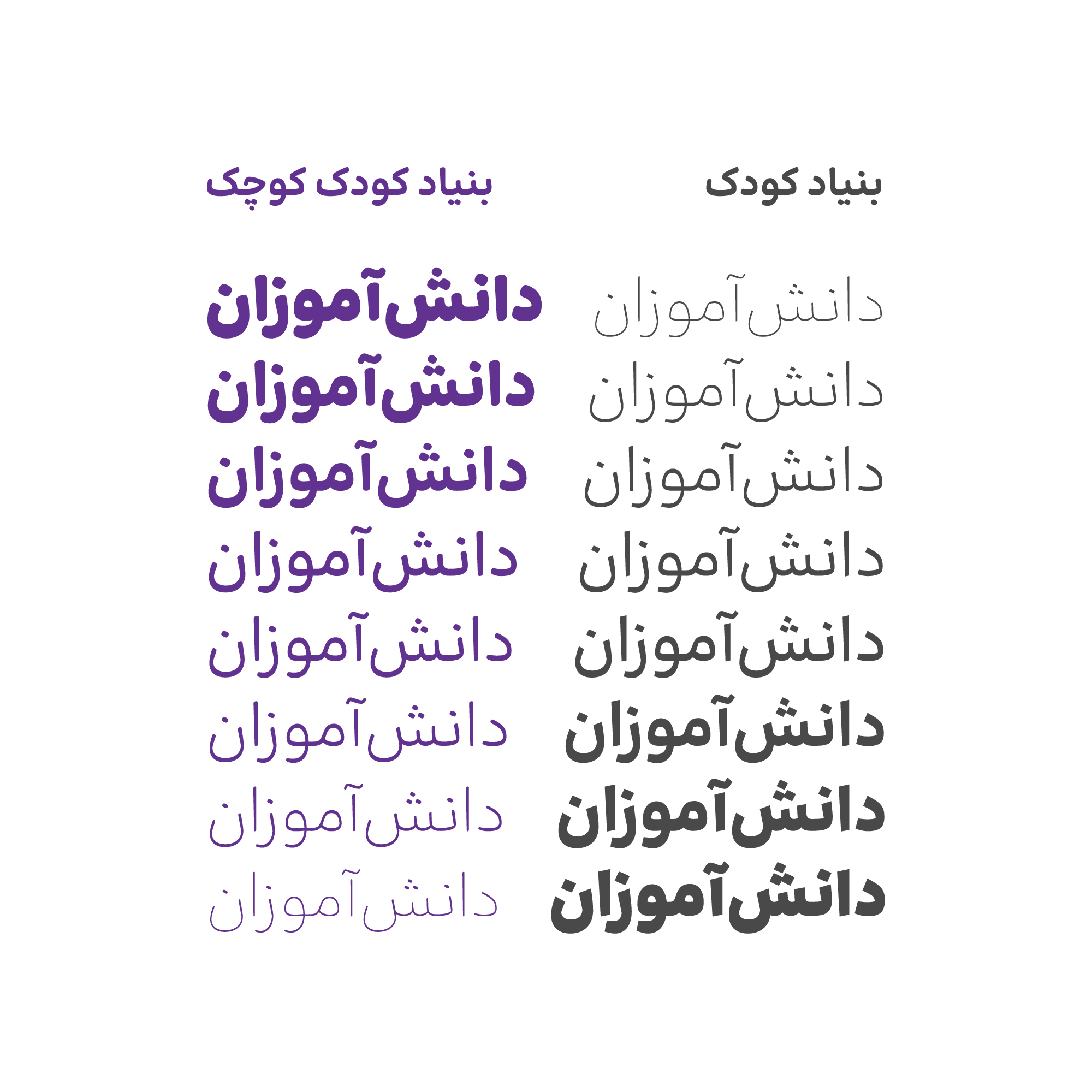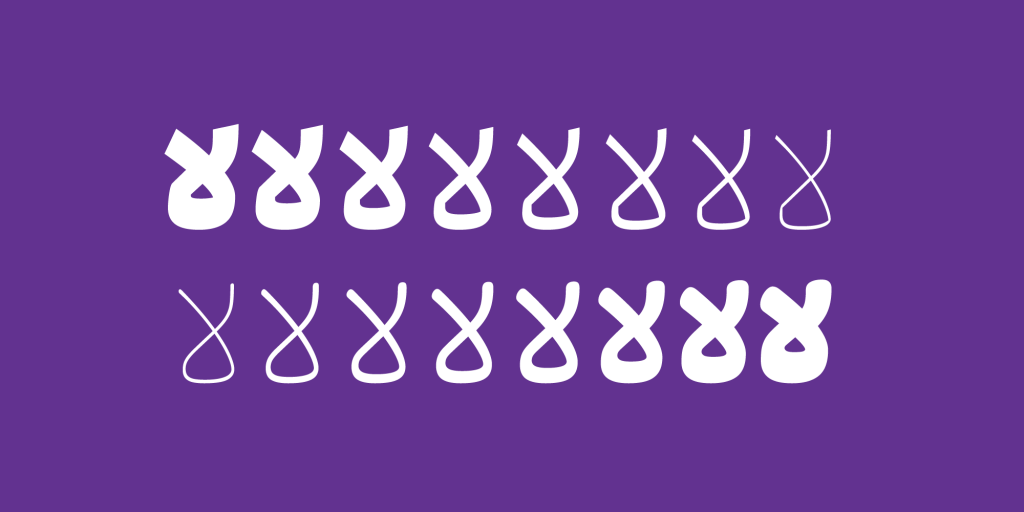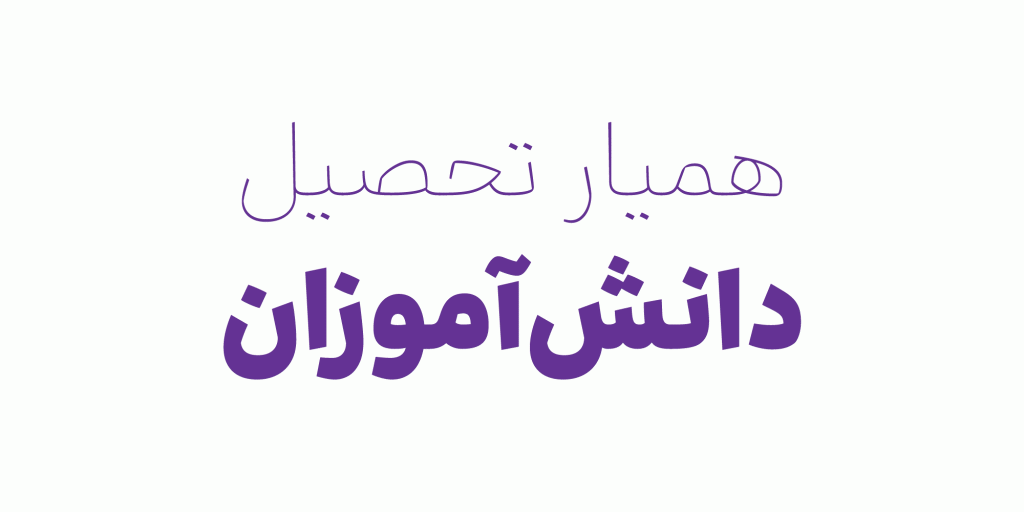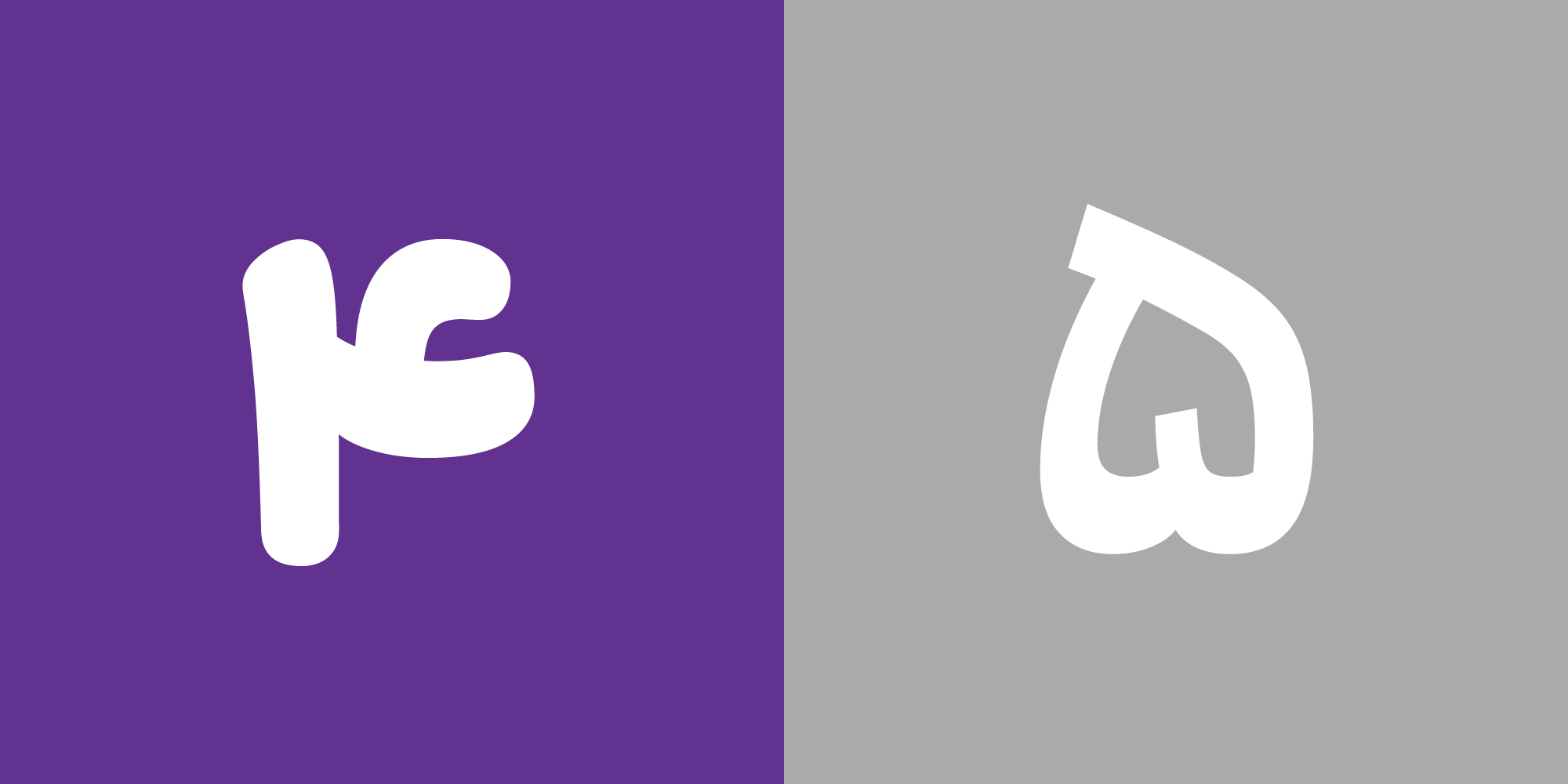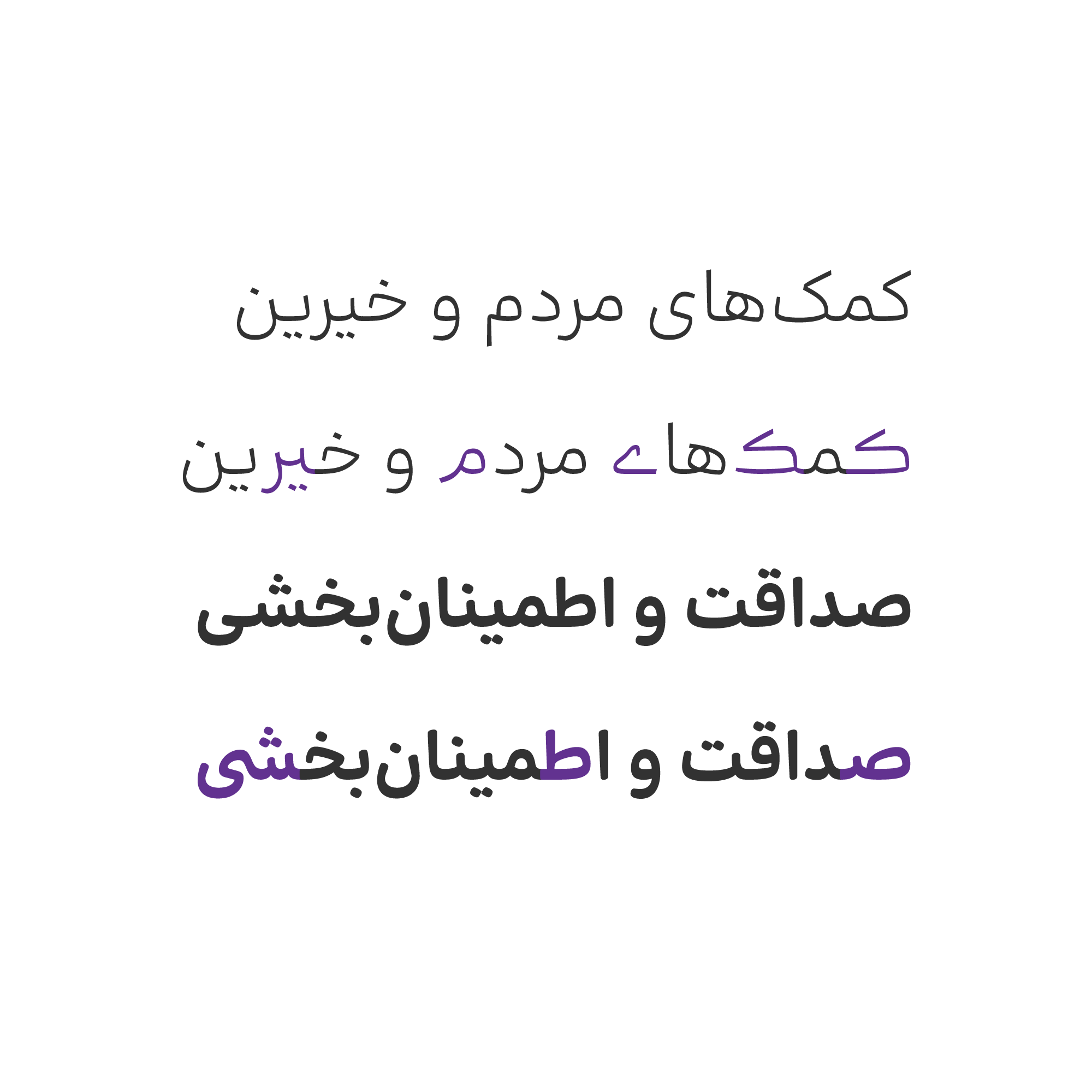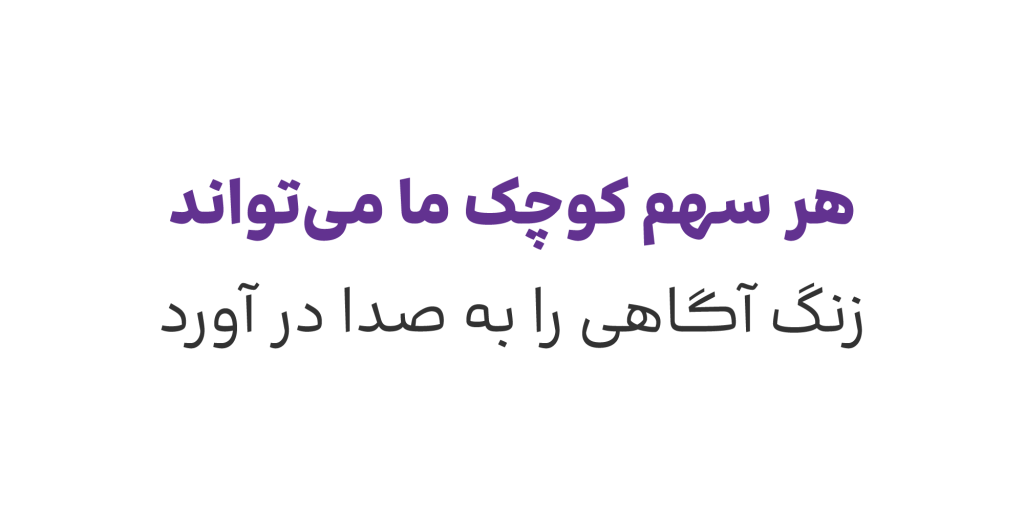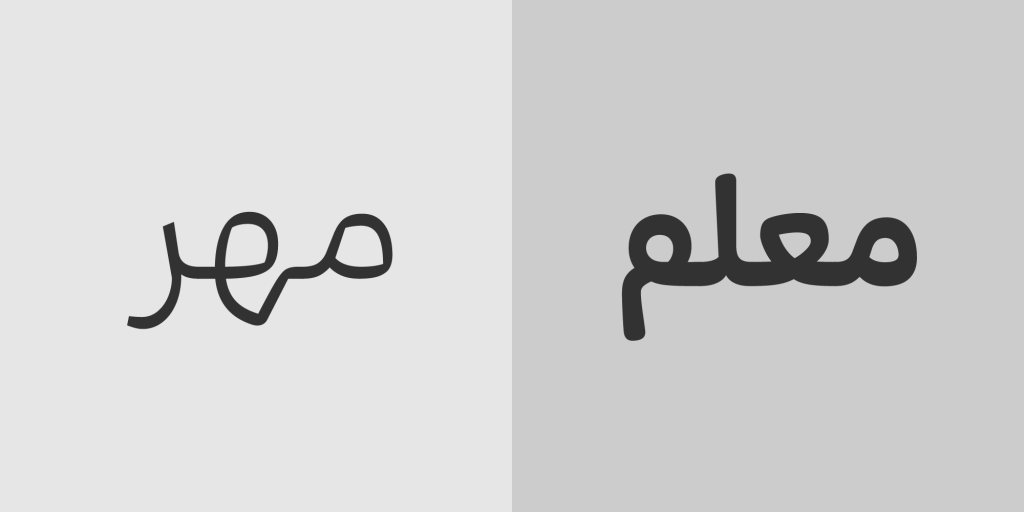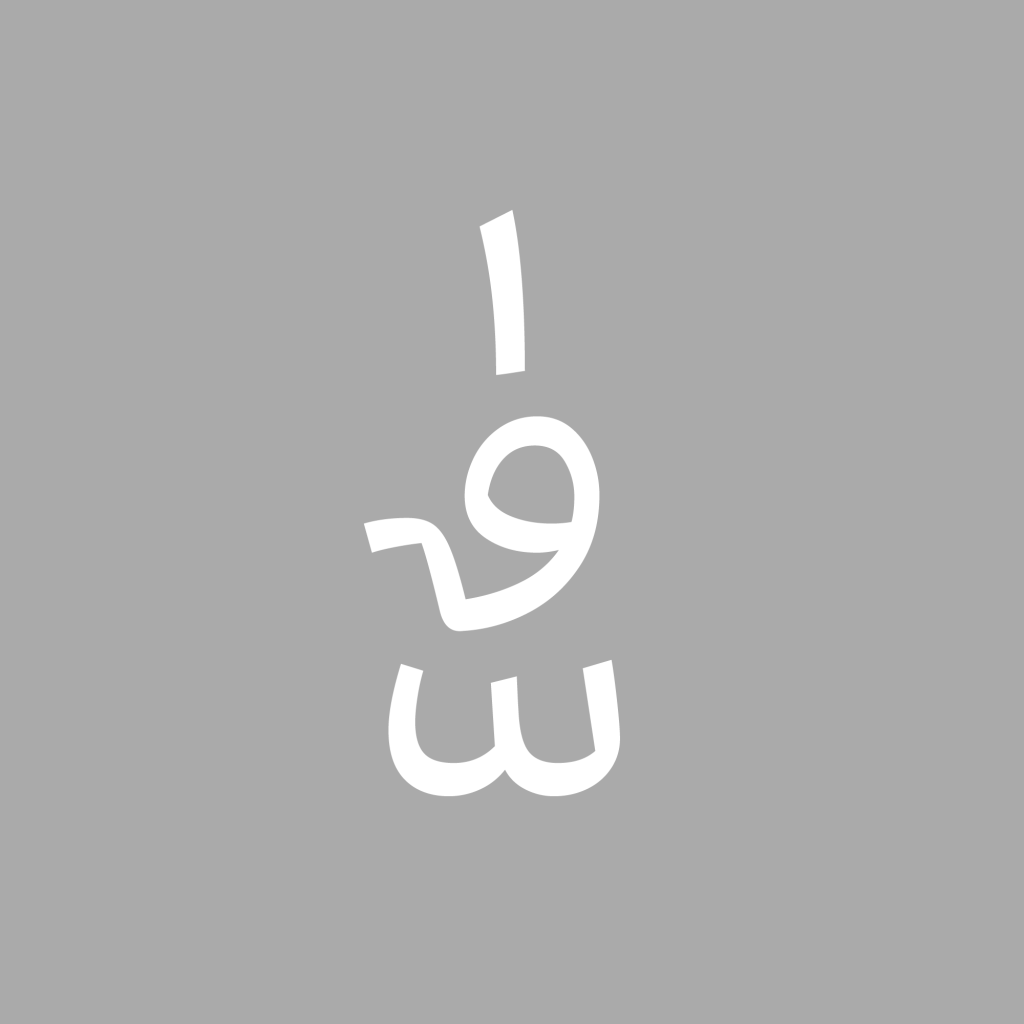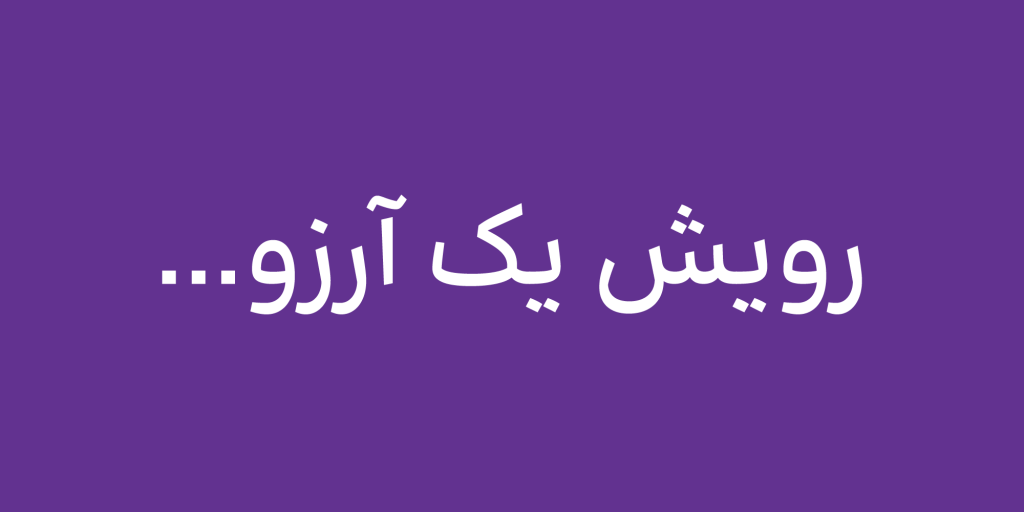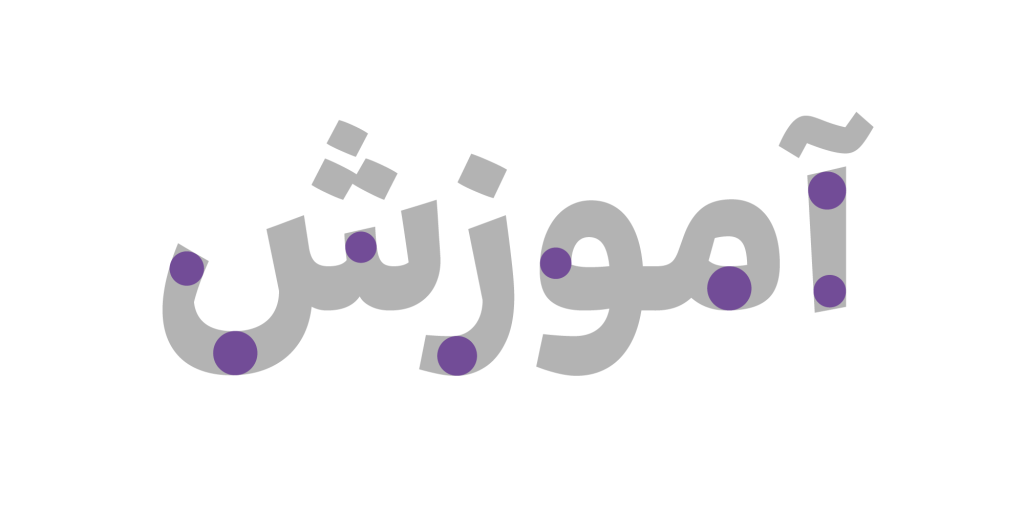
فونت بنیاد کودک
فونت بنیاد کودک قلمی با ساختار و فرم های ساده ای است. ساده و بی آلایش و مصمم که روحیه ای شاد و پرانرژی دارد مناسب برای انواع رسانه های چاپی و دیجیتال می باشد. این قلم در نوشته های طولانی و ریز خوانایی خود را کاملا حفظ می کند . در عناوین و تیترها دلبرانه است و بینندگان ومخاطبان را به خود جذب می نماید.
این قلم دارای دو سبک و استایل است شبک گرد که آن را کودک کوچک می نامیم که فضایی کودکانه و شیرین دارد و سبک معمولی. فرمهای این فونت ساده است و با داشتن چشمهای نسبتا بزرگ، دندانههای واضح و تناسبات آشنا، خواناست. در طراحی تایپ فیس بنیاد کودک بین فرمهای منحنی و صاف هماهنگی و تعادل لازم برقرار گردیده همانند فونت گذار به همین سبب می تواند بازه وسیع و گسترده ای را پوشش دهد.
تنوع اوزان در این تایپ فیس
این قلم با دارا بودن 8 وزن از خیلی نازک تا ضخیم دارای تنوع گسترده ای از اوزان مختلف می باشد. که برای خلق هر نوع از نوشته و طراحی دست شما را کاملا باز می گذارد. همچنین با پشتیبانی تکنولوژی نسخه متغییر و وریبل فونت می توانید هر 8 وزن و 2 سبک را فقط در یک فایل به سادگی هرچه تمام تر داشته باشید. هم سرعت بیشتر خصوصا در صفحات وب و هم حجم کمتر .
در طراحی فرم ها و ترکیبات جایگزین امکان خلق تنوع و زیبایی بیشتر به طراحان و استفاده کنندگان از این قلم داده شده. شما عزیزان می توانید با مشاهده فایل راهنمای استفاده از این ترکیبات در این تایپ فیس از این قابلیت زیبا بهره مند شوید. همچنین فارسی کردن اعداد لاتین و همعرض کردن اعداد نیز در این راهنما آموزش داده شده.
وریبل فونت: فونت متغیر دارای ۲ محور: Weight (وزن) و Round (نرمی).